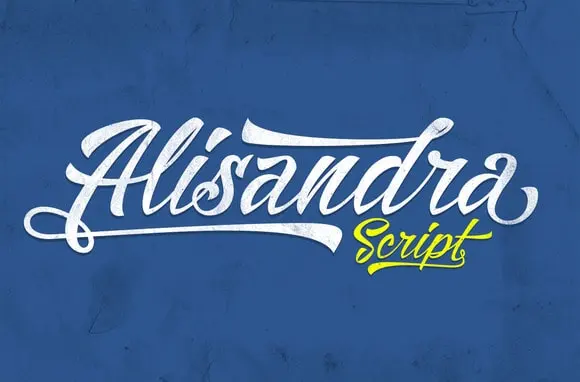
Alisandra Script Font – Download Grátis
A Alisandra Script Font é uma escolha perfeita para quem procura uma fonte de escrever que transmite beleza e elegância ao mesmo tempo. Designed por Mikrojihad, Inc., ela representa a arte da escrita manuscrita em seu auge, com linhas suaves e letras delicadas. A característica mais intrigante de Alisandra é sua paleta de swashes alternativos e caracteres extras, que adicionam profundidade ao design. Ideal para designers gráficos buscando um toque único ou para quem simplesmente adora arte da escrita manuscrita, a Alisandra Script Font oferece uma maneira refinada de incorporar personalidade em qualquer projeto visual. Além disso, o designer Hamilton compartilhou essa maravilha, tornando-a acessível e elegante para todos os amantes do design.